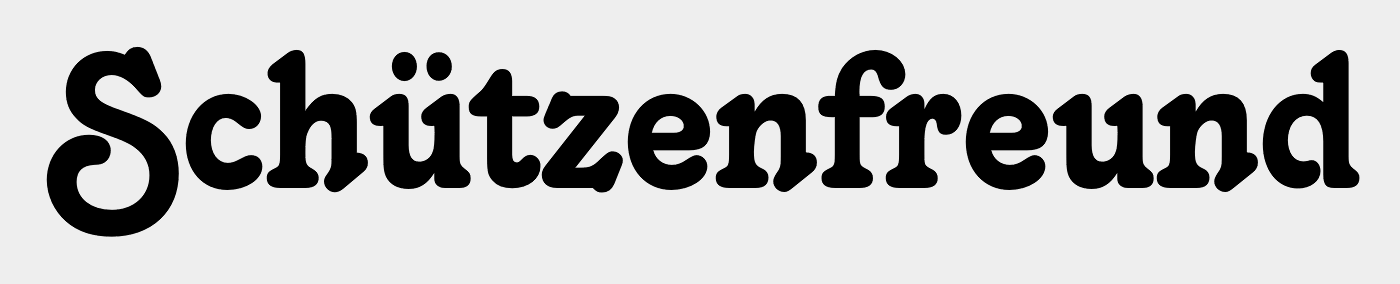
Suche Schriftart vom Logo "Schützenfreunde Burgheim"
Das sieht aus wie ein Autotrace (automatische Umwandlung eines Pixelbildes in Vektoren) einer "Cooper Black Swash". Die vielen unterschiedlichen "e" werden keinem Font entspringen.